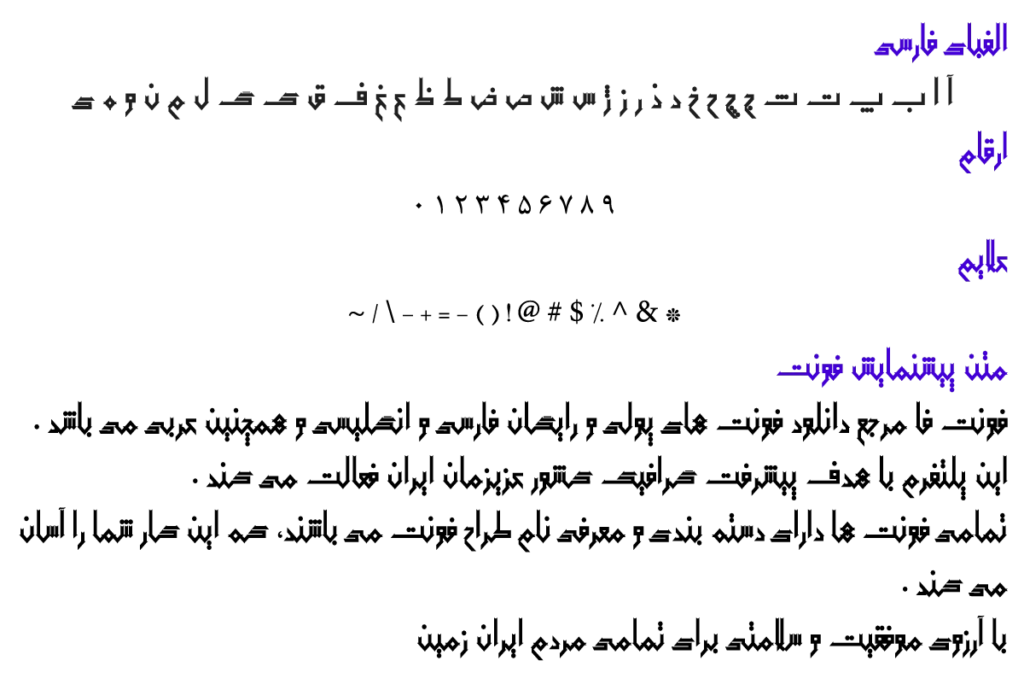
فونت فارسی زرقان حدیث – ZARGHAN HADITH
سال ساخت فونت: 1391
طراح فونت: ابراهیم شفیعی نوع فونت: فونت هندسی
پیشنمایش فونت زرقان حدیث
توضیحات و معرفی فونت زرقان حدیث
فونت فارسی زرقان حدیث ( ZARGHAN HADITH ) از مجموعه فونت های آزاد می باشد، همینطور نوع فونت هندسی می باشد.
فونت زیبای مرتبط توسط ابراهیم شفیعی در سال 1398 طراحی و ساخته شده است.
در تصویر زیر پیش نمایش این تایپ فیس را مشاهده میکنید.